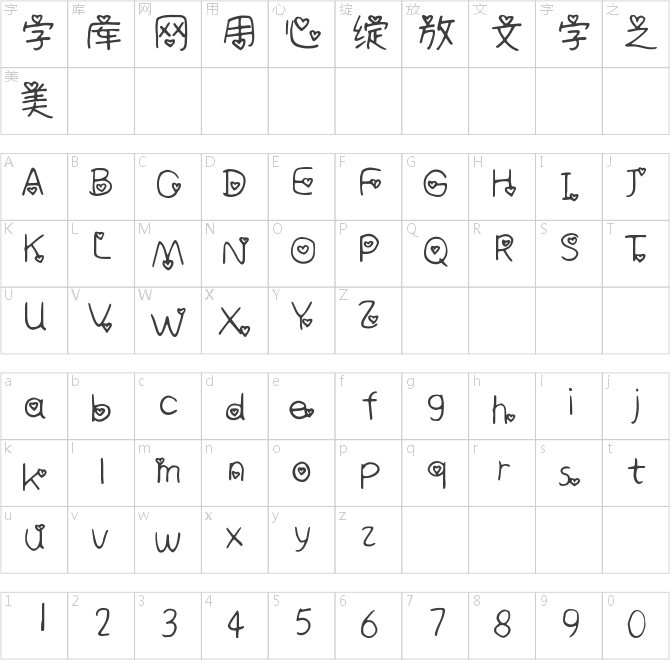
字體名稱: 倉(cāng)耳秘之果體
倉(cāng)耳秘之果體
倉(cāng)耳秘之果體介紹
倉(cāng)耳秘之果體字體字庫(kù)是一款讓人賞心悅目、百看不厭的中文字體,適合各類廣告和產(chǎn)品包裝設(shè)計(jì)應(yīng)用,字體大小6.02MB,格式為ttf字體,上傳用戶是白刃寒走得慢,作者/版權(quán)方為倉(cāng)耳字庫(kù)